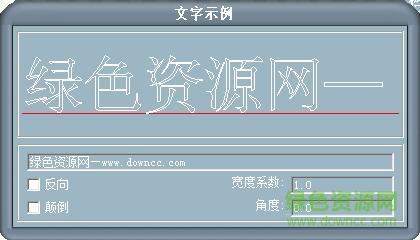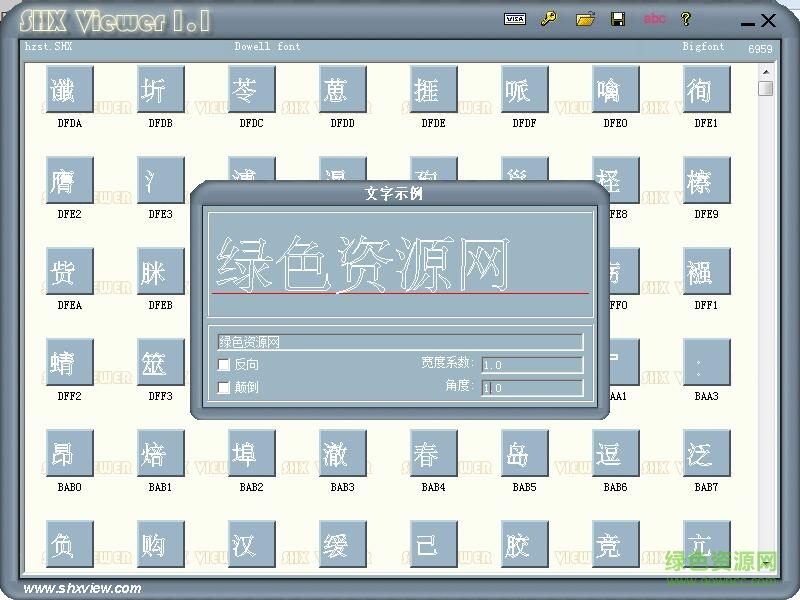
hzst.shx字體是一款不錯的cad字體,常被用來設(shè)計(jì)cad圖紙。這款字體外觀很正式,在建筑行業(yè)領(lǐng)域應(yīng)用廣泛。小編特地為大家提供了字體安裝方法,快來下載吧。
hzst.shx是一款在autocad軟件使用的宋體字體。用戶在打開CAD圖紙的時候,如果出現(xiàn)文字提示:“未找到字體hzst”,這是因?yàn)槟承﹫D紙打開需要此hzst字體的支持,才能看到具體文字內(nèi)容。大家可以在系統(tǒng)中安裝hzst.shx字體解決?。ňG色資源網(wǎng)小編推薦CAD字體大全,歡迎下載體驗(yàn)。)